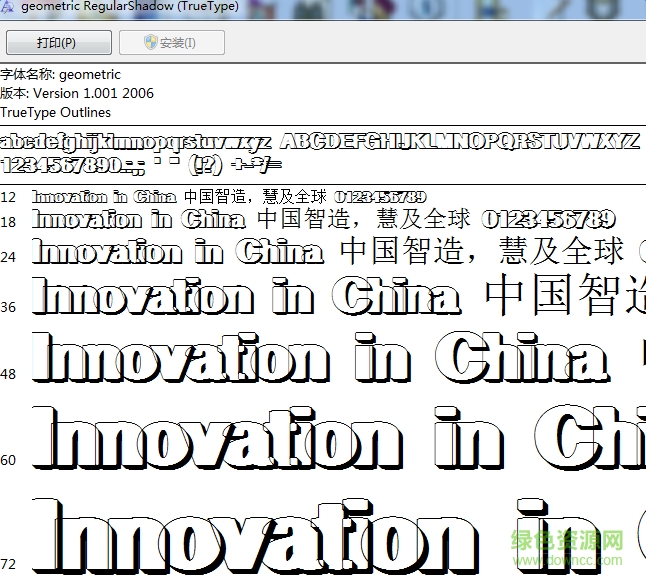
geometric字體是一款用于美工設計方面的英文字體,該字體個性非常鮮明,字體的整體效果非常出色,可以廣泛應用于出版印刷、文學雜志、宣傳海報、ppt、影視制作以及任何使用文字的領域,有需要的朋友可以免費下載收藏。
geometric字體是英文字體庫中的一款極具個性的字體,該字體的形體非常靈秀,整體十分嚴謹。適用于美工設計,有需要的用戶可以來綠色資源網(wǎng)下載使用!